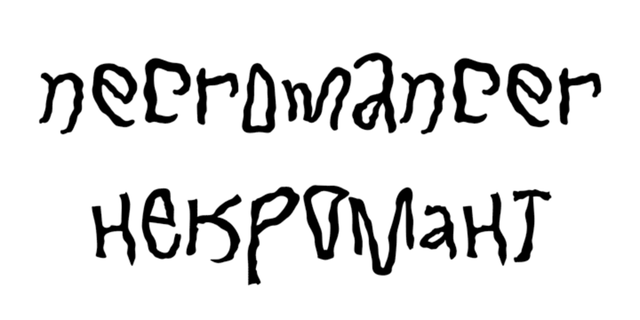
Шрифт Некромант разработан Андреем Кудрявцевым в 2012 году.
Ассоциации c семейством NecromantКачества и характер:
зловещий, злой, вампирский, кладбищенский, страшный, заразный, мертвый, фрик, адский, сумасшедший, странный, причудливый, оккультный, таинственный, загадочный, экспериментальный, жуткий, криповый, экзотичный, кричащий, вернакулярный, макабрический, психоделический, сумасбродный, динамичный
хоррор, ужастик, игра, анимация, развлечения, хэллоуин, аттракцион, вирус, болезнь, кладбище, заклинание, магия, проклятие, тату, монстр, чудовище, вампир, ведьма, зомби, жуки, пауки, насекомые, мертвец, призрак, привидение, Аддамсы, хеллоуин, Самайн, наклейка, стикер, металлист, концерт, электрогитара, квест, джокер Стилистика: